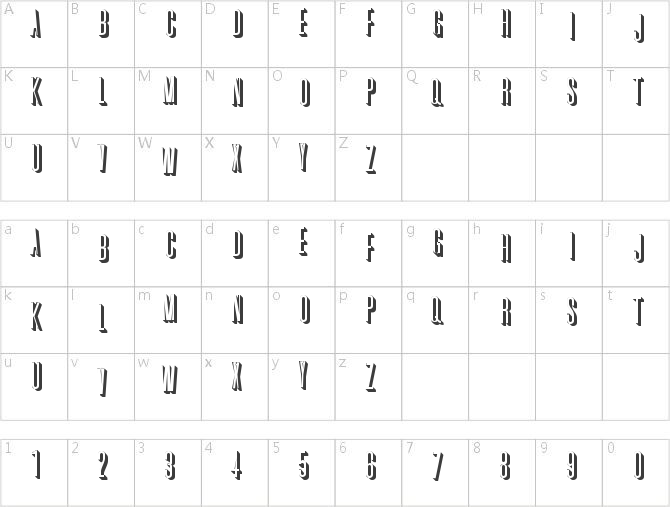
greatshadowregular
greatshadowregular介紹
greatshadowregular字體字庫是一款讓人賞心悅目、百看不厭的英文字體,適合各類廣告和產品包裝設計應用,字體大小0.05MB,格式為ttf字體,上傳用戶是快樂圍棋,作者/版權方為未知
greatshadowregular效果圖